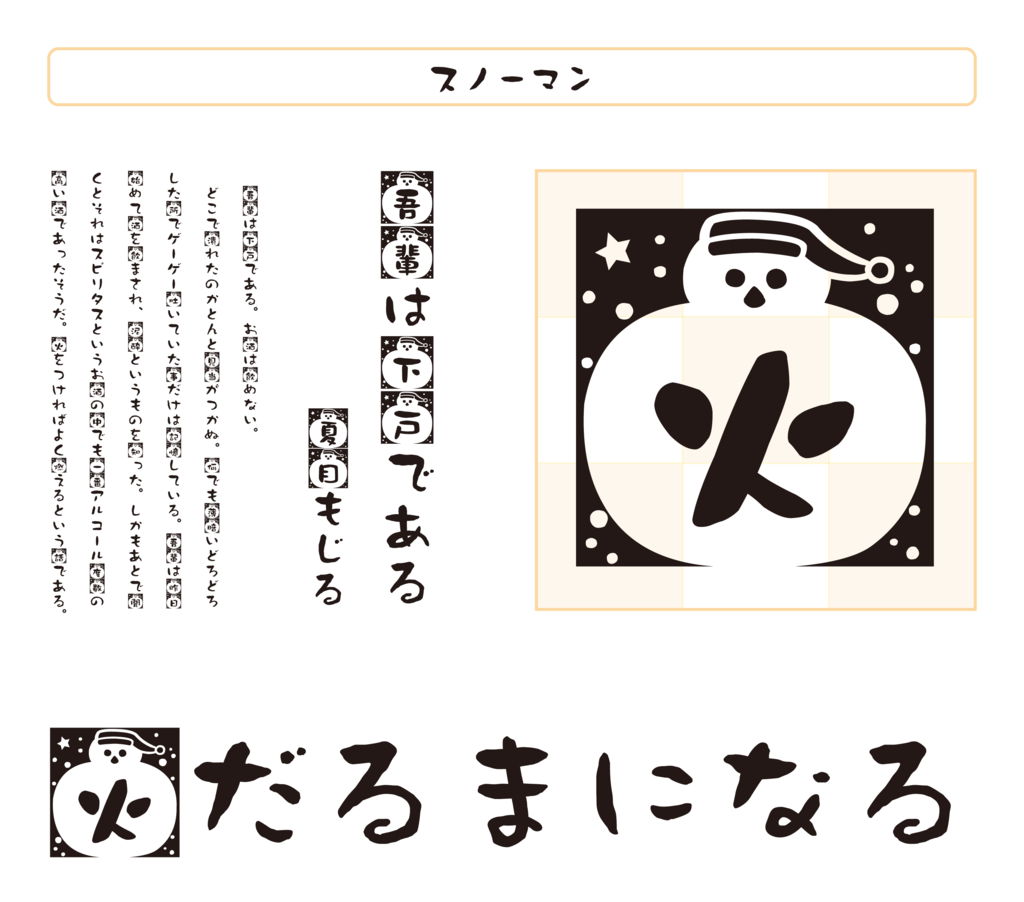
スノーマン
丸っこい墨文字の人気書体である「クラフト墨」をモチーフにした漢字が雪だるまになる謎フォント。
ダイナフォントは時おりツッコミを入れたくなるようなフォントがあるが、この「スノーマン」はいつ、どこで使用するのが正しいのだろうか。やはり冬や雪山、雪だるまなど「雪」関連で使用するのがベストか。